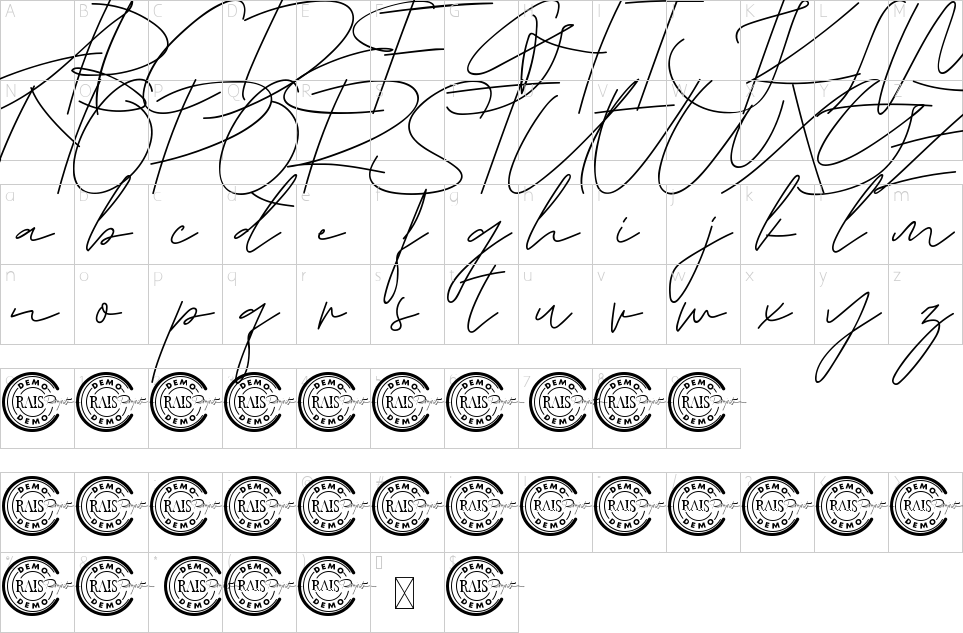
Descubra Joseline Kayle, uma fonte elegante e moderna ideal para estilos de design gráfico variados. Esta fonte foi criada pelo designer desconhecido RaisProject, e já foi baixada 244 vezes. Joseline Kayle é uma escolha perfeita para designers que procuram uma fonte com um certo charme, capaz de dar um toque especial a qualquer projeto. Com sua aparência fluida e sua variedade de caracteres, Joseline Kayle é um recurso gráfico valioso que será uma ótima opção para personalizar sua marca ou criar um design visual impecável. Baixe-a agora e descubra por si mesmo a qualidade e versatilidade desta fonte.